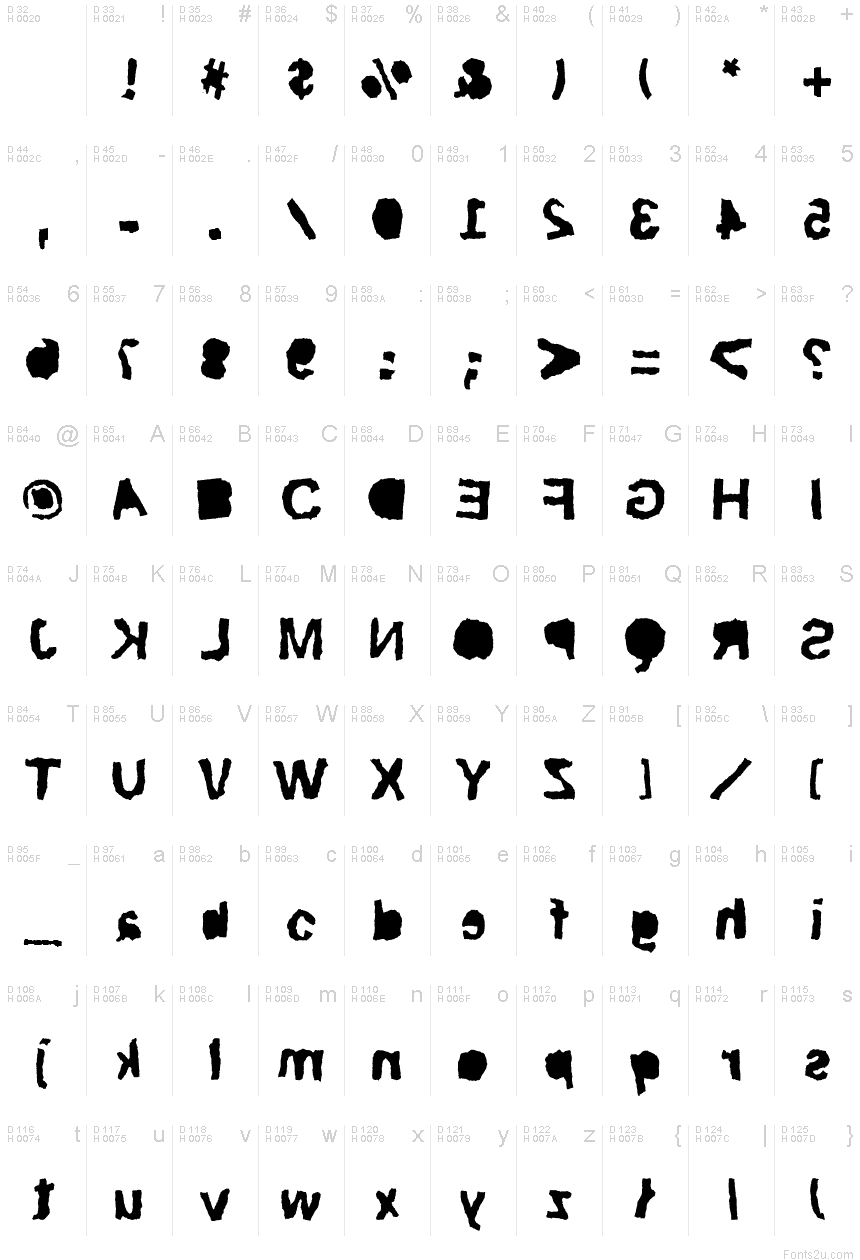
ripTRASH von Manuel Viergutz ist eine kostenlose, verwitterte Display-Schrift mit rauen, zerrissenen Silhouetten. Ihre schweren Buchstaben haben ausgefranste Kanten und ungleichmäßige Stellen, die an gealterte Tinte oder zerrissenes Papier erinnern. Die Formen sind direkt und kraftvoll.
Diese zerrissene Papiertextur verbindet Schriften unmittelbar mit Collagen, fotokopierten Kunstwerken und rauer Musikfotografie. Sie eignet sich für Konzertplakate und Albumcover, während ihre unregelmäßige Masse auch auf Streetwear-Merchandise Sinn ergibt. Für Branding könnten die gealterten Formen Teil eines Emblems für ein Underground-Label, einen Skateshop oder einen unabhängigen Musikclub werden.
“rip TRASH” ist eine Demo-Schrift mit sechs Schnitten: Regular, Mirror, Cut, Cut Mirror, Round und Round Mirror. Sie enthält 100 Glyphen, einschließlich akzentuierter Zeichen.